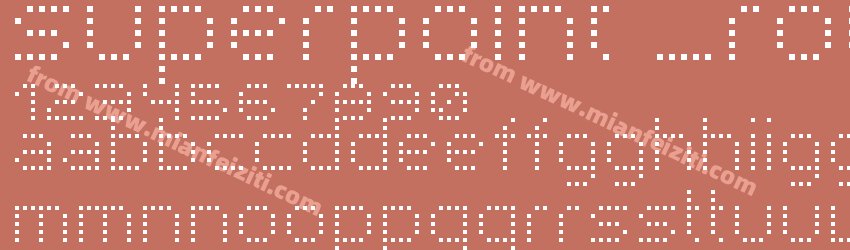
superpoint _rounded
字体名称: superpoint _rounded
Postscript名称: Superpointrounded
字体版本: Macromedia Fontographer 4.1.5 07.10.2001
字体字重: _rounded
本款“superpoint _rounded”是一款书写很新颖的字体,字体大方,适合各种设计作品使用!欢迎下载!